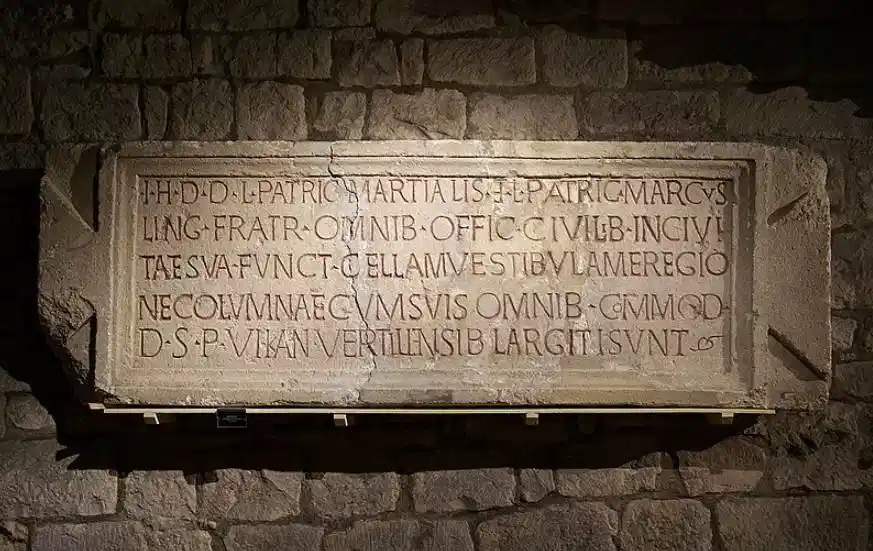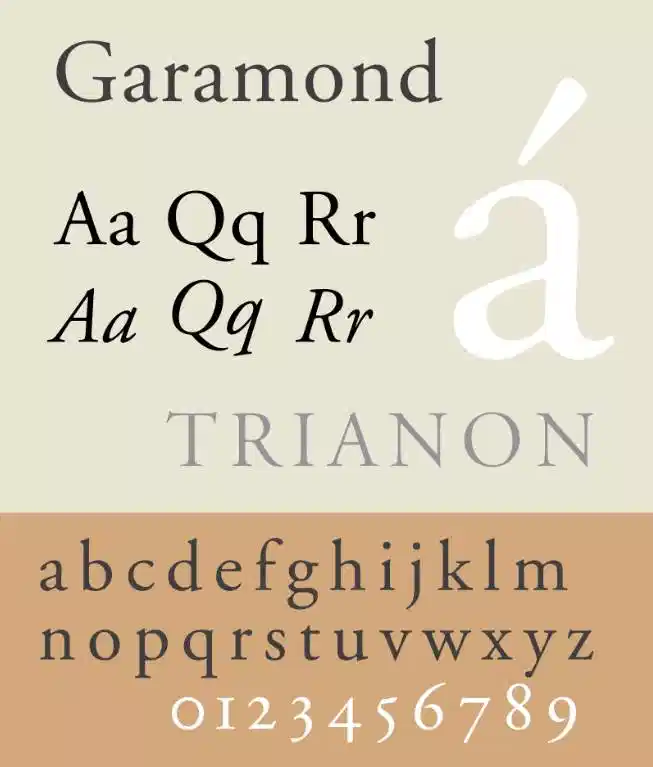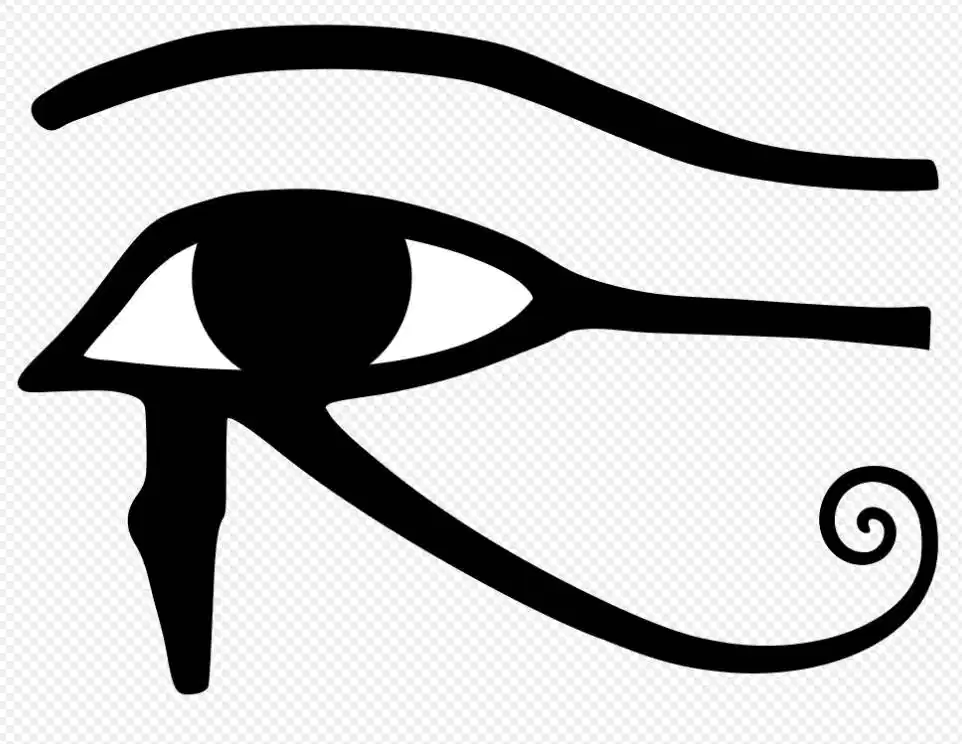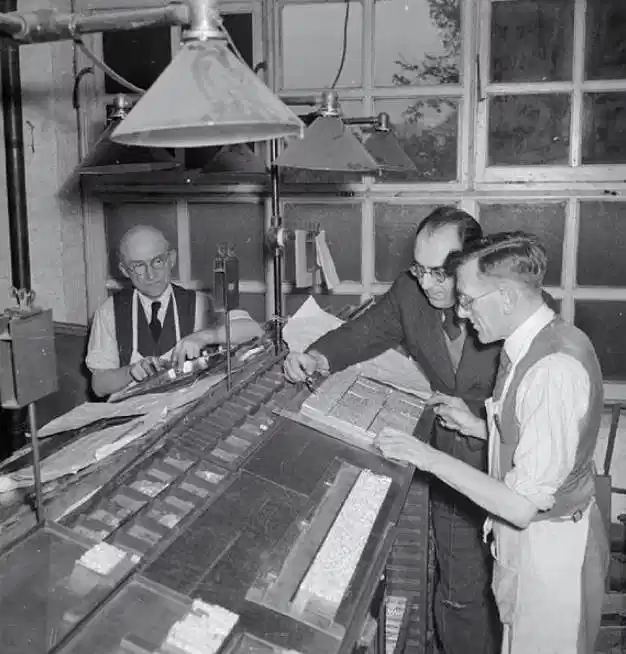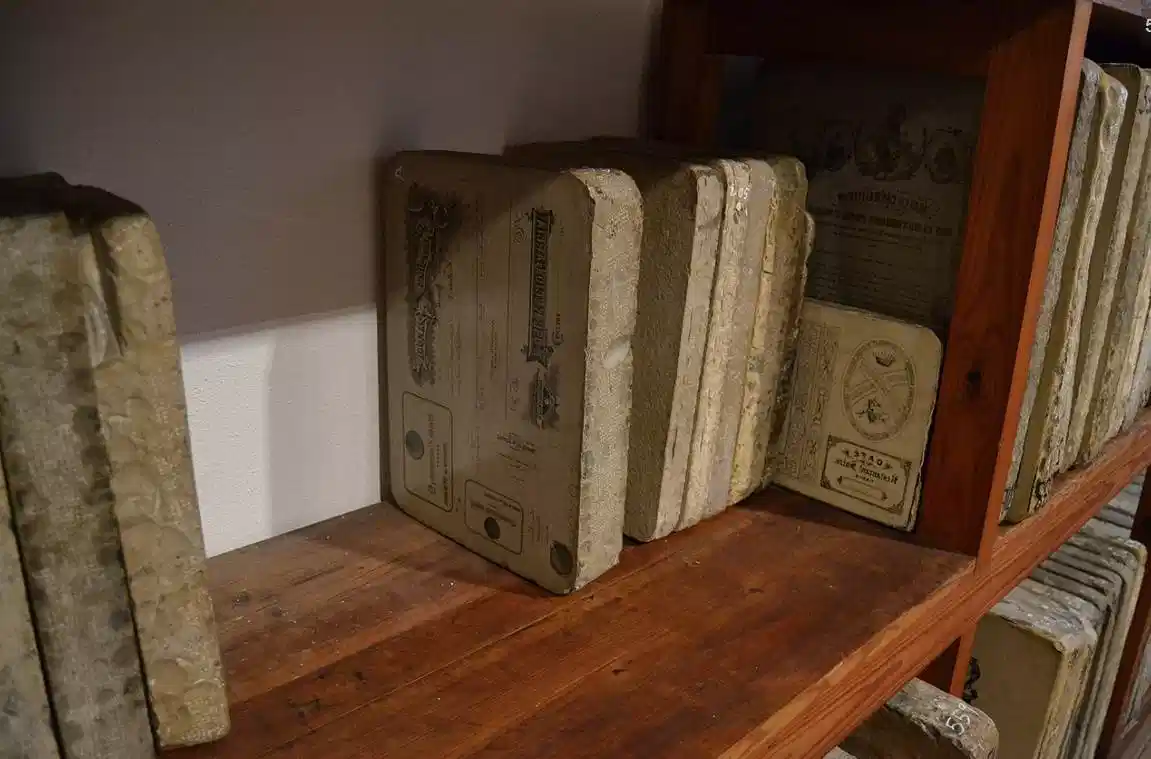
Explorez l'évolution fascinante de la typographie, des premières formes d'écriture à l'invention de Gutenberg et jusqu'aux innovations numériques contemporaines. Découvrez les figures clés, les mouvements artistiques et les enjeux actuels de cet art essentiel
Ce point explore la longue transition entre les premières formes d'écriture et l'invention de la typographie, qui a révolutionné la diffusion des textes.
L'écriture n'est pas apparue du jour au lendemain. C'est un processus lent et progressif qui s'est étalé sur des millénaires.
On distingue plusieurs étapes clés :
Les pictogrammes constituent les premières formes d'écriture connues, remontant au Néolithique, il y a plus de 5000 ans. Ils consistent en des dessins figuratifs représentant des objets concrets du monde réel, tels que le soleil, un arbre, un animal ou un outil. Utilisés notamment en Mésopotamie et en Égypte, ils permettaient de communiquer des informations simples et directes. Cependant, leur principal inconvénient réside dans leur incapacité à exprimer des concepts abstraits, des idées complexes ou des actions, limitant ainsi leur portée et leur capacité à transmettre des messages nuancés. Cette limitation a conduit à l'évolution vers des systèmes d'écriture plus sophistiqués.
Les idéogrammes marquent une évolution par rapport aux pictogrammes en représentant non plus un objet concret, mais une idée ou un concept abstrait. Par exemple, le dessin d'un soleil peut symboliser la lumière, le jour, la chaleur ou même le temps. Cette abstraction permet d'exprimer des notions plus complexes que les simples objets. Néanmoins, les idéogrammes conservent une certaine ambiguïté et leur nombre important rend leur apprentissage et leur utilisation complexes. Ils constituent une étape importante vers des systèmes d'écriture plus performants, mais restent encore limités dans leur capacité à exprimer toute la richesse du langage.
Apparue en Mésopotamie vers 3200 av. J.-C., l'écriture cunéiforme est considérée comme la première véritable forme d'écriture organisée. Elle utilise des signes en forme de clous ou de coins, imprimés sur des tablettes d'argile à l'aide d'un calame, un roseau taillé. Ce système mixte combine des idéogrammes, représentant des idées, et des signes phonétiques, représentant des sons. Cette combinaison permet une plus grande précision et une plus large gamme d'expression. L'écriture cunéiforme a été utilisée pendant plusieurs millénaires et a servi à transcrire plusieurs langues, marquant une avancée majeure dans l'histoire de l'écriture.
Utilisés à partir de 3200 av. J.-C. en Égypte, les hiéroglyphes constituent un système d'écriture complexe et sophistiqué. Ils combinent trois types de signes : des idéogrammes, représentant des concepts ; des phonogrammes, représentant des sons ; et des signes déterminatifs, qui précisent le sens d'un mot et évitent les ambiguïtés. Ce système complexe nécessitait un apprentissage long et approfondi, le réservant à une élite de scribes. Les hiéroglyphes ont joué un rôle déterminant dans la conservation de la culture et de l'histoire égyptiennes, gravés sur les monuments, les papyrus et les objets rituels.
L'alphabet représente une invention majeure attribuée aux Phéniciens vers le XIIe siècle av. J.-C. Son principe fondamental est de représenter chaque son (ou phonème) par un signe unique, une consonne dans l'alphabet phénicien. Les Grecs ont ensuite adopté et adapté cet alphabet en y ajoutant les voyelles, le rendant plus complet et plus précis. L'alphabet grec est à l'origine de l'alphabet latin, qui est aujourd'hui le système d'écriture le plus utilisé au monde. L'alphabet a considérablement simplifié l'écriture, la rendant plus accessible et favorisant ainsi la diffusion du savoir et de la culture.
Le support d'écriture a une influence directe sur la forme et l'évolution de l'écriture :
Les tablettes d'argile, largement utilisées en Mésopotamie dès le IVe millénaire av. J.-C., offraient un support d'écriture à la fois durable et économique. L'argile, abondante dans la région, était façonnée en tablettes humides sur lesquelles les scribes imprimaient des signes cunéiformes à l'aide d'un calame. Une fois séchées au soleil ou cuites au four, ces tablettes devenaient extrêmement résistantes au temps, ce qui explique leur conservation jusqu'à nos jours. L'écriture cunéiforme, avec ses marques en forme de coins, était particulièrement bien adaptée à ce support, permettant une inscription claire et durable. Les tablettes d'argile ont ainsi servi de support pour une grande variété de textes : administratifs, littéraires, religieux et scientifiques.
Inventé en Égypte, le papyrus est un support d'écriture fabriqué à partir de la plante du même nom, le Cyperus papyrus. Les tiges de papyrus étaient découpées en fines lamelles, puis assemblées et pressées pour former des feuilles. Plus léger et plus maniable que l'argile, le papyrus permettait l'écriture à l'encre, à l'aide d'un pinceau ou d'un roseau taillé. Ce support a favorisé le développement de l'écriture et la diffusion du savoir dans l'Égypte antique et au-delà. Cependant, le papyrus est plus fragile que l'argile et se conserve moins bien dans des conditions humides.
Le parchemin, fabriqué à partir de peau d'animal (généralement de mouton, de chèvre ou de veau) spécialement traitée, offre un support d'écriture de qualité supérieure. Plus résistant et plus souple que le papyrus, il permettait l'écriture sur les deux faces et pouvait être plié et relié pour former des livres, les codex. Le parchemin est devenu le support d'écriture privilégié au Moyen Âge, supplantant progressivement le papyrus en Europe. Sa robustesse et sa durabilité ont permis la conservation de nombreux textes importants de cette époque. Le parchemin, bien que plus coûteux à produire que le papyrus, offrait une meilleure qualité et une plus grande longévité.
Avant l'invention de l'imprimerie, tous les textes étaient copiés à la main. La calligraphie, l'art de la belle écriture, occupait une place importante :
L'onciale est un style d'écriture en lettres capitales arrondies, caractérisé par des formes douces et cursives. Utilisée principalement entre le IVe et le VIIIe siècle, elle était particulièrement adaptée à l'écriture sur des supports souples comme le parchemin, avec une plume d'oie taillée en biseau. Ses lettres rondes et sans angles vifs permettaient une écriture plus rapide et plus fluide que les capitales romaines classiques. L'onciale a été largement employée pour la copie de textes bibliques et d'autres ouvrages religieux, contribuant à la diffusion du christianisme. Bien qu'elle ait progressivement décliné face à la caroline, elle a influencé les écritures ultérieures, notamment pour les lettrines et les débuts de chapitres.
La caroline, apparue sous l'impulsion de Charlemagne au VIIIe siècle, représente une rupture majeure dans l'histoire de l'écriture occidentale. Elle se distingue par sa grande lisibilité et sa régularité, grâce à des lettres claires, distinctes et bien proportionnées. La caroline a introduit une distinction claire entre les majuscules et les minuscules, facilitant grandement la lecture et la compréhension des textes. Cette écriture a été diffusée dans tout l'Empire carolingien, contribuant à l'unification culturelle et à la renaissance intellectuelle de l'époque. La caroline est considérée comme l'ancêtre direct de nos minuscules actuelles, et son influence est encore visible dans les caractères d'imprimerie que nous utilisons aujourd'hui.
L'écriture gothique, qui s'est développée à partir du XIIe siècle, marque une évolution stylistique importante par rapport à la caroline. Elle se caractérise par des lettres anguleuses, brisées et verticales, créant un effet visuel dense et ornemental. L'écriture gothique a connu plusieurs variations régionales et stylistiques, telles que la textura, la rotunda, la schwabacher et la fraktur. Elle a été largement utilisée au Moyen Âge pour la copie de manuscrits, les documents officiels et les textes littéraires. Bien que considérée aujourd'hui comme moins lisible que la caroline, l'écriture gothique a marqué son époque et a influencé l'art et l'architecture de la période gothique.
La xylographie est une technique d'impression qui consiste à graver une image ou un texte en relief sur une planche de bois. La planche est ensuite encrée et pressée sur un support (papier ou tissu) pour reproduire l'image ou le texte.
La xylographie a vu le jour en Chine dès le VIIe siècle, sous la dynastie Tang. Elle s'est ensuite progressivement diffusée vers l'ouest, atteignant l'Europe au XIVe siècle, notamment grâce aux échanges commerciaux le long de la Route de la Soie. En Europe, la xylographie a connu un essor important, étant employée pour la production d'images religieuses, souvent vendues comme des objets de piété, de cartes à jouer, très populaires à l'époque, et d'ouvrages illustrés, les "livres xylographiques" ou "incunables xylographiques". Cette technique a ainsi contribué à la diffusion des images et des textes avant l'invention de l'imprimerie à caractères mobiles.
La xylographie a joué un rôle déterminant dans l'évolution des techniques d'impression et a ouvert la voie à l'invention de la typographie par Gutenberg au XVe siècle. En effet, la pratique de la xylographie a permis de comprendre les principes fondamentaux de l'impression en relief, tels que la préparation de la matrice, l'encrage et le pressage sur un support. Les artisans ont ainsi pu développer des techniques d'encrage plus efficaces et perfectionner les presses utilisées pour l'impression. Néanmoins, la xylographie présentait une limitation majeure : chaque page, texte et image, nécessitait la gravure d'une nouvelle planche de bois, ce qui rendait le processus coûteux, long et laborieux, notamment pour les ouvrages de grande taille.
Ce développement permet de comprendre le contexte historique et technique qui a mené à l'invention de la typographie par Gutenberg au XVe siècle, marquant une rupture majeure dans l'histoire de la communication et de la diffusion du savoir.
Ce point central aborde l'invention qui a bouleversé la diffusion de l'information et du savoir en Europe et dans le monde.
Johannes Gutenberg, orfèvre allemand né à Mayence vers 1400, est considéré comme l'inventeur de la typographie moderne. Son innovation majeure réside dans la mise au point des caractères mobiles en plomb.
Son processus, fruit de plusieurs années de recherche, combine plusieurs éléments clés :
Gutenberg a révolutionné la fabrication des caractères d'imprimerie en développant un système ingénieux. Il créa des moules en métal, appelés matrices, dans lesquels il coulait un alliage de plomb, d'étain et d'antimoine. Cet alliage, fusible à basse température et suffisamment résistant pour l'impression, permettait de reproduire chaque caractère (lettre, chiffre, signe de ponctuation) à l'identique et en grande quantité. Cette standardisation des caractères fut une innovation majeure, rendant possible la composition et la recomposition à l'infini des textes. Ce procédé permettait une production beaucoup plus rapide et efficace que la gravure sur bois utilisée auparavant.
Pour imprimer les textes composés avec ses caractères mobiles, Gutenberg adapta une presse en bois, inspirée des presses à vin ou des pressoirs agricoles. Cette presse permettait d'appliquer une pression uniforme sur les caractères encrés et le papier, assurant ainsi une impression nette et homogène. L'adaptation de cette technologie existante à l'imprimerie fut une étape fondamentale. Elle permettait d'exercer une force importante et contrôlée, indispensable pour transférer l'encre des caractères au papier. Cette invention a marqué une avancée technique majeure dans le domaine de l'impression.
Gutenberg a également mis au point une encre spécifique pour l'impression typographique. Cette encre, grasse à base d'huile, était beaucoup plus visqueuse que l'encre utilisée pour l'écriture manuscrite. Cette viscosité était essentielle pour obtenir une impression nette et durable sur le papier, empêchant l'encre de baver et assurant un bon transfert sur le support. La composition de cette encre fut un élément clé du succès de l'imprimerie de Gutenberg. Elle assurait une qualité d'impression supérieure et une meilleure conservation des textes imprimés.
Le composteur est un outil essentiel dans le processus d'impression typographique. Il s'agit d'un instrument permettant d'aligner et de maintenir les caractères mobiles en métal afin de former des lignes de texte. Le typographe utilisait le composteur pour assembler les caractères un par un, en suivant le texte à imprimer. Une fois la ligne composée, elle était transférée sur une galée, un plateau métallique, pour former des colonnes de texte, puis une page entière. Le composteur a donc permis d'organiser et de structurer le texte avant l'impression, assurant une mise en page précise et ordonnée.
L'ensemble de ces innovations constitue un système complet et performant qui permet l'impression de textes en grande quantité et à moindre coût par rapport à la copie manuscrite.
La Bible de Gutenberg, également connue sous le nom de Bible à 42 lignes en raison du nombre de lignes de texte par page, est une œuvre monumentale. Elle représente le premier livre imprimé en Europe grâce à la technique des caractères mobiles inventée par Gutenberg. Imprimée entre 1454 et 1455 à Mayence, en Allemagne, cette bible est un jalon majeur dans l'histoire du livre. Elle symbolise la révolution de l'imprimerie et le passage d'une culture manuscrite à une culture imprimée. Son importance historique et culturelle est immense, marquant le début d'une nouvelle ère dans la diffusion du savoir.
Environ 180 exemplaires de la Bible de Gutenberg ont été imprimés lors de sa première édition. Ce nombre, considérable pour l'époque, témoigne de la capacité de production offerte par l'imprimerie à caractères mobiles. Parmi ces exemplaires, une quarantaine ont été imprimés sur parchemin, un support plus coûteux et plus prestigieux que le papier. L'utilisation du parchemin conférait à ces exemplaires une qualité et une durabilité exceptionnelles. La majorité des exemplaires ont été imprimés sur papier, ce qui a permis une diffusion plus large de l'ouvrage.
La Bible de Gutenberg est reconnue pour la qualité exceptionnelle de son impression. La régularité des caractères, la netteté des traits et la parfaite superposition des encres témoignent du savoir-faire de Gutenberg et de son équipe. La mise en page soignée, avec ses marges harmonieuses et sa typographie élégante, contribue à la beauté de l'ouvrage. Chaque page est un chef-d'œuvre de précision et d'esthétisme, reflétant le souci du détail et la maîtrise technique de Gutenberg. Cette qualité d'impression a servi de modèle pour les imprimeurs des générations suivantes.
La Bible de Gutenberg marque une étape majeure dans l'histoire du livre et de la diffusion du savoir. Son impression a permis une production de livres beaucoup plus rapide et moins coûteuse que la copie manuscrite. Cette innovation a rendu les livres plus accessibles et a contribué à la diffusion des idées et des connaissances à une échelle sans précédent. La Bible de Gutenberg a ainsi joué un rôle essentiel dans la Renaissance et la Réforme, en permettant la circulation des textes religieux et des idées nouvelles. Elle a ouvert la voie à l'imprimerie moderne et à la société de l'information que nous connaissons aujourd'hui.
Après l'invention de Gutenberg, l'imprimerie se diffuse rapidement en Europe, notamment grâce à la dispersion des compagnons de Gutenberg après des difficultés financières.
Les premiers livres imprimés en Europe entre l'invention de Gutenberg et l'année 1500 sont appelés incunables, terme dérivé du latin "incunabula" qui signifie "berceau". Cette appellation souligne le caractère inaugural de ces ouvrages, marquant les débuts balbutiants de l'imprimerie typographique. Les incunables se caractérisent souvent par une imitation des manuscrits médiévaux, tant dans leur mise en page que dans leur typographie. Ils témoignent de la transition entre l'ère du manuscrit et l'ère de l'imprimé. Ils constituent aujourd'hui de précieux témoignages de cette période charnière de l'histoire du livre.
Après l'invention de Gutenberg et les difficultés financières qui ont suivi, notamment le sac de Mayence en 1462, les compagnons et les ouvriers formés par Gutenberg se sont dispersés à travers l'Europe, emportant avec eux leur savoir-faire. Des ateliers d'imprimerie ont ainsi vu le jour dans les grandes villes européennes, devenant rapidement des centres importants de production de livres. Des villes comme Venise, Paris, Cologne, Nuremberg, Strasbourg et Bâle sont devenues des foyers majeurs de l'imprimerie, contribuant à la diffusion rapide de cette nouvelle technologie à travers le continent. Cette dispersion a permis une expansion géographique rapide de l'imprimerie.
L'imprimerie a joué un rôle capital dans l'essor de l'humanisme et de la Renaissance. En permettant la reproduction rapide et à moindre coût des textes, elle a favorisé la diffusion des œuvres des auteurs antiques, redécouverts par les humanistes. Elle a également permis la circulation des nouvelles idées et des découvertes scientifiques, stimulant les débats intellectuels et les échanges entre les savants. L'imprimerie a ainsi contribué à transformer en profondeur la culture et la société européennes, en rendant le savoir plus accessible et en favorisant l'émergence d'une opinion publique. Elle a été un vecteur essentiel de la diffusion des idées nouvelles de la Renaissance.
la diffusion du savoir et la Réforme : L'invention de l'imprimerie a eu des conséquences considérables sur la société et la culture :
L'invention de l'imprimerie a révolutionné la diffusion du savoir en permettant la production massive de livres. Auparavant coûteux et rares, les livres deviennent plus accessibles à un public plus large, favorisant ainsi l'alphabétisation. Cette diffusion des connaissances a stimulé les échanges intellectuels, les débats et les découvertes. L'imprimerie a ainsi contribué à l'émergence d'une société plus instruite et plus ouverte aux idées nouvelles. Elle a permis une démocratisation du savoir sans précédent.
L'imprimerie a joué un rôle important dans la normalisation et la standardisation des langues vernaculaires. En diffusant des textes écrits dans ces langues, elle a contribué à fixer leur orthographe, leur grammaire et leur vocabulaire. L'imprimerie a ainsi favorisé le passage d'une multitude de dialectes locaux à des langues nationales plus unifiées. Ce processus a renforcé les identités culturelles et nationales en Europe. Elle a permis une plus grande cohérence et une meilleure compréhension des textes à travers les régions.
L'imprimerie a été un facteur déterminant dans la diffusion des idées de Martin Luther et de la Réforme protestante au XVIe siècle. Les écrits de Luther, traduits en langues vernaculaires et imprimés en grande quantité, ont touché un large public, remettant en question l'autorité de l'Église catholique. Cette diffusion rapide des idées réformatrices a contribué à la division religieuse de l'Europe. L'imprimerie a ainsi joué un rôle majeur dans un bouleversement religieux et politique majeur.
L'imprimerie a favorisé l'émergence d'une opinion publique en permettant la diffusion rapide et à grande échelle des idées et des débats. Les pamphlets, les journaux et les autres imprimés ont permis la circulation des informations et des opinions, encourageant les discussions et les échanges. Cette circulation de l'information a contribué à la formation d'une conscience collective et à l'émergence d'un espace public de discussion. L'imprimerie a ainsi joué un rôle clé dans le développement de la pensée critique et de la participation citoyenne.
En somme, l'invention de la typographie par Gutenberg a marqué un tournant majeur dans l'histoire de l'humanité. Elle a révolutionné la communication, la diffusion du savoir et a eu des conséquences profondes sur la société, la culture et la politique.
Cette période est marquée par une évolution stylistique importante des caractères typographiques, passant des formes inspirées de l'écriture manuscrite à des formes de plus en plus géométriques et contrastées.
Au XVe siècle, en Italie, les humanistes, passionnés par la redécouverte des textes antiques, ont développé une nouvelle forme d'écriture manuscrite : l'écriture humanistique. Cette écriture, en rupture avec l'écriture gothique alors dominante, se caractérisait par une clarté et une lisibilité renforcées. Inspirée des inscriptions romaines antiques, elle privilégiait des formes rondes et équilibrées, plus faciles à lire que les caractères gothiques anguleux. Cette nouvelle esthétique reflétait l'idéal humaniste de retour aux sources de la culture classique. L'écriture humanistique a ainsi préparé le terrain à une révolution typographique.
Les premiers imprimeurs italiens, notamment Nicolas Jenson à Venise, ont puisé leur inspiration dans l'écriture humanistique pour créer les caractères typographiques dits "romains". Ces caractères se distinguaient par plusieurs éléments clés : les empattements, petites extensions aux extrémités des lettres, le contraste modéré entre les pleins et les déliés (traits épais et fins), et une grande lisibilité. Ces caractéristiques rendaient la lecture plus agréable et plus efficace. Les caractères romains ont rapidement supplanté les caractères gothiques dans l'imprimerie, marquant une étape importante dans l'histoire de la typographie.
En rompant avec les formes gothiques, jugées trop complexes et peu lisibles, elle a ouvert la voie à une esthétique plus classique et plus harmonieuse. Les caractères romains, inspirés de cette écriture, ont incarné cet idéal de clarté et d'équilibre. Cette évolution a profondément influencé l'évolution de la typographie occidentale, les caractères romains étant encore largement utilisés aujourd'hui. L'héritage de l'écriture humanistique continue ainsi de façonner notre perception de la lecture et de l'écriture.
Claude Garamond (vers 1480-1561) est une figure majeure de l'histoire de la typographie. Graveur de caractères et imprimeur français, il est considéré comme l'un des plus grands typographes de tous les temps. Son travail a profondément influencé l'évolution des caractères d'imprimerie. Il a notamment créé des caractères romains d'une qualité exceptionnelle, qui ont connu un succès retentissant à travers l'Europe. Son héritage perdure encore aujourd'hui, témoignant de son génie et de son impact durable sur le monde de l'imprimerie.
Garamond a créé des caractères romains d'une grande élégance et d'une lisibilité remarquable. Ces caractères se distinguent par leur finesse, leur équilibre et leur harmonie. Les formes des lettres sont claires et bien proportionnées, facilitant la lecture et rendant les textes imprimés plus agréables à l'œil. Cette recherche de la perfection esthétique et fonctionnelle a contribué au succès durable de ses créations. Son travail a établi un nouveau standard de qualité dans le domaine de la typographie.
Les caractères de Garamond ont été utilisés pendant des siècles et continuent d'inspirer les typographes contemporains. De nombreuses versions numériques de ses caractères existent aujourd'hui, permettant de les utiliser sur les ordinateurs et dans les logiciels de mise en page. Ces versions numériques perpétuent l'héritage de Garamond et permettent à ses créations de continuer à influencer le monde de la typographie. Son influence est telle qu'elle marque durablement l'histoire de la typographie, en établissant un standard de qualité et d'élégance qui continue de résonner aujourd'hui.
John Baskerville et la recherche de la perfection typographique :
Au XVIIIe siècle, le typographe anglais John Baskerville (1706-1775) apporte des innovations importantes dans la conception des caractères typographiques.
John Baskerville, typographe anglais du XVIIIe siècle (1706-1775), ne s'est pas limité à la création de caractères. Il a également cherché à améliorer l'ensemble du processus d'impression. Pour cela, il a développé une nouvelle technique de fabrication du papier, plus lisse et plus uniforme, permettant une meilleure impression. Il a également perfectionné la presse à imprimer, afin d'obtenir une pression plus homogène sur le papier. Ces innovations ont contribué à améliorer significativement la qualité des impressions, en rendant les textes plus nets et plus précis.
Baskerville est surtout connu pour la création de caractères typographiques dits de "transition". Ces caractères marquent une évolution importante entre les caractères romains classiques, hérités de la Renaissance, et les caractères modernes, qui apparaîtront à la fin du XVIIIe siècle. Les caractères de Baskerville se caractérisent par un contraste plus marqué entre les pleins (traits épais) et les déliés (traits fins), des empattements plus fins et plus horizontaux, et une plus grande régularité des formes. Ces évolutions ont conféré aux caractères une apparence plus élégante et plus raffinée.
Baskerville accordait une importance primordiale à la lisibilité et à l'esthétique de ses caractères. Il recherchait un équilibre parfait entre la forme et la fonction, considérant que la beauté d'un caractère devait servir sa lisibilité. Il a ainsi conçu des caractères à la fois élégants et faciles à lire, ce qui a contribué à leur succès et à leur influence durable. Son souci du détail et sa recherche de l'harmonie ont fait de ses caractères des modèles du genre, influençant profondément l'évolution de la typographie. Son approche a marqué un tournant dans la conception des caractères.
À la fin du XVIIIe siècle et au début du XIXe siècle, les typographes français Firmin Didot (1764-1836) et italien Giambattista Bodoni (1740-1813) ont révolutionné la typographie en développant un nouveau style de caractères, appelé "moderne" ou "Didone". Ce style marquait une rupture nette avec les caractères précédents, en introduisant une esthétique plus géométrique et contrastée. Didot et Bodoni, bien que travaillant indépendamment, ont abouti à des résultats similaires, définissant les canons du style moderne. Leur influence sur la typographie a été considérable et durable.
Les caractères Didot et Bodoni se caractérisent par un contraste très marqué entre les pleins (traits épais) et les déliés (traits fins), créant un effet visuel saisissant. Leurs empattements sont fins et droits, souvent en forme de filets, renforçant l'aspect géométrique. La structure générale des lettres est rigoureuse et précise, dégageant une impression de clarté et de modernité. Ces caractéristiques confèrent aux textes composés en Didot ou Bodoni une élégance formelle et une grande lisibilité, tout en soulignant leur aspect graphique.
Les caractères Didot et Bodoni ont connu un immense succès dès leur apparition et ont influencé la typographie pendant une grande partie du XIXe siècle. Leur esthétique novatrice a séduit les imprimeurs et les éditeurs, qui les ont largement utilisés dans les livres, les journaux et les affiches. Bien que leur popularité ait connu des fluctuations au cours du XXe siècle, ils sont encore utilisés aujourd'hui, notamment dans la presse de luxe, la publicité et l'édition d'art, où leur élégance et leur raffinement sont particulièrement appréciés. Leur héritage continue d'inspirer les designers graphiques contemporains.
L'émergence du style moderne a marqué une rupture significative avec les formes typographiques plus traditionnelles, telles que les caractères romains de Garamond ou les caractères de transition de Baskerville. En privilégiant le contraste, la géométrie et la rigueur, les caractères Didot et Bodoni ont ouvert la voie à une nouvelle esthétique typographique. Cette évolution annonçait la tendance vers des caractères de plus en plus géométriques et contrastés, qui se poursuivra au cours du XIXe et du XXe siècle, notamment avec l'avènement des caractères linéales (sans-serif).
Cette période du XVIe au XVIIIe siècle est, par conséquent, primordiale pour l'histoire de la typographie. Elle voit l'évolution des caractères romains inspirés de l'écriture humanistique, l'émergence des caractères classiques de Garamond, la transition vers des formes plus contrastées avec Baskerville, et enfin l'apparition du style moderne avec Didot et Bodoni. Ces évolutions ont façonné l'esthétique typographique et continuent d'influencer la création de caractères aujourd'hui.
Le XIXe siècle marque une nouvelle étape majeure dans l'histoire de l'imprimerie et de la typographie, avec l'avènement de l'industrialisation et l'apparition de nouvelles techniques et de nouveaux styles.
Ces deux inventions ont profondément transformé les techniques de reproduction d'images et de textes :
Inventée par Alois Senefelder à la fin du XVIIIe siècle, laLa lithographie est une technique d'impression à plat qui utilise une pierre calcaire. L'image est dessinée sur la pierre avec un crayon gras, puis la pierre est traitée chimiquement pour que l'encre adhère uniquement aux parties dessinées. Ce procédé permet une grande finesse de trait et la reproduction d'images complexes, ouvrant la voie à l'illustration de masse et à l'art de l'affiche. La lithographie a permis la diffusion d'images à grande échelle et a eu un impact majeur sur l'art et la communication visuelle. Elle a notamment favorisé l'essor de l'illustration de livres et de la publicité.
Développée au milieu du XIXe siècle, la photogravure a permis de reproduire des images photographiques par des procédés d'impression typographique. Un cliché photographique est transféré sur une plaque de métal (zinc ou cuivre), qui est ensuite gravée chimiquement. Cette technique permet une reproduction fidèle des détails et des nuances de gris des photographies, révolutionnant l'illustration des livres et des journaux. La photogravure a rendu possible l'intégration des photographies dans les supports imprimés, ouvrant de nouvelles perspectives pour l'information et la communication. Elle a marqué une étape essentielle dans l'histoire de la reproduction d'images.
L'automatisation de la composition typographique a permis d'accroître considérablement la vitesse et la productivité de l'imprimerie :
Inventée par Ottmar Mergenthaler en 1886, la Linotype a révolutionné l'industrie de l'imprimerie en automatisant la composition des textes. Son nom, "line-o'-type" (ligne de caractères), décrit parfaitement son fonctionnement : la machine fond des lignes de texte entières en plomb. L'opérateur tape le texte sur un clavier, et la machine assemble automatiquement les matrices des caractères et les fond en une ligne de plomb prête à l'impression. Cette innovation a considérablement accéléré la production de journaux et de livres, rendant l'impression beaucoup plus rapide et économique. La Linotype a permis une diffusion massive de l'information imprimée.
Inventée par Tolbert Lanston en 1887, la Monotype propose une approche différente de la composition typographique automatisée. Au lieu de fondre des lignes entières, elle fond des caractères individuels en plomb, qui sont ensuite assemblés en lignes de texte. Cette méthode offre une plus grande flexibilité que la Linotype, car elle permet de composer des textes complexes avec des caractères de différentes tailles et de différents styles. La Monotype était particulièrement adaptée aux travaux d'impression de haute qualité, tels que les livres d'art et les éditions soignées. Elle a permis une grande précision dans la mise en page et l'utilisation de caractères variés.
Le XIXe siècle voit l'apparition de nouvelles familles de caractères, qui reflètent les évolutions esthétiques et les besoins de la publicité et de l'industrie :
Les égyptiennes, également appelées "slab serif" en anglais, font leur apparition au début du XIXe siècle. Elles se caractérisent par des empattements rectangulaires et épais, leur donnant un aspect massif et affirmé. Ce style typographique évoque l'Égypte antique, alors très en vogue, et a été largement utilisé dans la publicité et l'affichage. Leur forte présence visuelle les rendait idéales pour attirer l'attention et pour les titres percutants. Les égyptiennes ont marqué une rupture avec les styles précédents par leur géométrie et leur impact visuel.
Les antiques, ou "old style", s'inspirent des inscriptions grecques et romaines, renouant avec l'esthétique des caractères classiques. Elles se caractérisent par des empattements triangulaires et un contraste modéré entre les pleins et les déliés. Ce style typographique offre une grande lisibilité et une élégance sobre, ce qui les rendait particulièrement adaptées aux textes courants et aux ouvrages de littérature. Les antiques ont perpétué l'héritage des caractères humanistiques et ont continué à être utilisées tout au long du XIXe siècle. Elles incarnent une certaine tradition typographique.
Les linéales, ou "sans serif" (sans empattements), apparaissent également au XIXe siècle, bien que leur popularité explose au XXe siècle avec l'essor du design moderne. Elles se distinguent par l'absence d'empattements, ce qui leur confère une grande simplicité et une lisibilité renforcée, notamment pour les textes courts et les affiches. Les linéales sont devenues un standard pour les titres, la signalétique et les supports numériques, grâce à leur aspect épuré et contemporain. Elles symbolisent la modernité et l'efficacité dans la communication visuelle. Leur influence est encore très présente dans le design actuel.
Les mouvements artistiques de l'Art Nouveau (fin XIXe - début XXe siècle) et de l'Art Déco (années 1920-1930) ont également influencé la typographie :
L'Art Nouveau, qui s'épanouit entre la fin du XIXe et le début du XXe siècle, est un mouvement artistique caractérisé par des formes organiques, des lignes courbes et une forte inspiration de la nature. Cette esthétique se retrouve également en typographie, où elle se traduit par des caractères ornés, sinueux et décoratifs. Les lettres s'inspirent souvent de formes végétales, avec des arabesques et des volutes. Cette typographie expressive et imaginative était particulièrement utilisée dans les affiches, les titres et les ouvrages d'art. L'Art Nouveau a apporté une grande richesse ornementale à la typographie.
L'Art Déco, qui connaît son apogée dans les années 1920-1930, se distingue par des formes géométriques, des lignes droites et un style plus épuré. En typographie, cela se traduit par des caractères aux formes géométriques, contrastées et élégantes. Les lettres adoptent des formes angulaires, des lignes droites et des motifs stylisés. L'Art Déco privilégie la clarté, la symétrie et l'harmonie des proportions. Cette typographie, souvent utilisée dans la publicité, l'architecture et le design industriel, reflète l'esprit de modernité et de sophistication de l'époque. Elle marque une rupture avec l'exubérance de l'Art Nouveau.
Le XIXe siècle a donc été une période de profondes transformations pour l'imprimerie et la typographie. L'invention de nouvelles techniques d'impression, l'automatisation de la composition et l'apparition de nouvelles familles de caractères ont permis une production massive de textes et d'images, et ont contribué à l'essor de la presse, de la publicité et de la culture de masse.
Le XXe siècle est une période de profonds changements pour la typographie, marquée par l'influence du modernisme, l'essor de la publicité, l'arrivée de nouvelles technologies et la diversification des styles.
Le Bauhaus, école d'art et de design fondée en Allemagne en 1919, a eu une influence majeure sur la typographie du XXe siècle.
Le Bauhaus, fondé en Allemagne en 1919, a profondément marqué l'histoire du design et de la typographie. L'école prônait une esthétique fonctionnelle, rationnelle et géométrique, en rupture radicale avec les ornements et les décorations caractéristiques de l'Art Nouveau. Cette approche mettait l'accent sur la simplicité des formes, la clarté des lignes et l'adéquation de la forme à la fonction. Cette philosophie a influencé tous les domaines du design, de l'architecture aux arts graphiques, et a eu un impact durable sur la typographie moderne. Le Bauhaus a cherché à créer un langage visuel universel et accessible.
Des figures emblématiques du Bauhaus, comme Herbert Bayer et Jan Tschichold, ont joué un rôle essentiel dans le développement des caractères linéales (sans empattements). Ils ont créé des polices aux formes simples et épurées, telles que l'Universal (Bayer) et le Futura (Paul Renner, influencé par le Bauhaus), qui sont devenues des classiques du design typographique. Ces caractères se caractérisent par leur géométrie rigoureuse, leur absence d'ornements et leur grande lisibilité. Ils ont incarné l'idéal du Bauhaus d'une typographie fonctionnelle et moderne. Leur influence est encore visible dans de nombreuses polices contemporaines.
Le Bauhaus a également innové en promouvant l'utilisation combinée de la photographie et de la typographie. Cette approche a permis la création de compositions graphiques dynamiques et innovantes, où le texte et l'image interagissent de manière nouvelle. L'utilisation du photomontage et de la typographie en tant qu'éléments graphiques à part entière a ouvert de nouvelles perspectives dans le domaine de la communication visuelle. Le Bauhaus a ainsi contribué à l'émergence du graphisme moderne, en explorant les possibilités offertes par la combinaison de différents médias. Cette approche a profondément influencé la publicité et le design graphique.
L'influence du Bauhaus se retrouve dans le développement du style typographique international, qui a dominé le design graphique pendant une grande partie du XXe siècle. Ce style privilégie la clarté, la lisibilité et la fonctionnalité, en accord avec les principes du Bauhaus. Les caractères linéales sont devenus un standard, et la mise en page se caractérise par une grille rigoureuse et une hiérarchie visuelle claire. L'héritage du Bauhaus continue d'influencer le design contemporain, en particulier dans les domaines de la typographie, du graphisme et de l'architecture. Son impact sur la culture visuelle est indéniable.
Le XXe siècle a vu l'essor de la publicité et du marketing, qui ont eu un impact important sur la typographie.
L'essor de la publicité au XXe siècle a profondément influencé la typographie, en créant un besoin de caractères spécifiques, plus expressifs et plus accrocheurs. L'objectif principal de la publicité étant d'attirer l'attention du public et de promouvoir un produit ou un service, la typographie a dû s'adapter pour devenir un outil de persuasion visuelle. Les caractères sont devenus plus audacieux, plus originaux et plus distinctifs afin de se démarquer dans un paysage visuel de plus en plus saturé. Cette exigence a stimulé la création de nouvelles formes typographiques et l'expérimentation de styles variés. La typographie est ainsi devenue un élément essentiel de la stratégie publicitaire.
Pour répondre aux besoins spécifiques de la publicité, de nouvelles familles de caractères ont été créées au XXe siècle. Parmi celles-ci, on peut citer les caractères à empattements gras, comme le Clarendon, qui offrent une forte présence visuelle et une grande lisibilité, idéales pour les titres et les slogans publicitaires. On a également vu l'émergence de caractères décoratifs, souvent inspirés de styles historiques, tels que les caractères égyptiens revisités, ou influencés par les mouvements artistiques comme l'Art Déco, avec ses formes géométriques et élégantes. Ces nouvelles familles ont élargi le champ des possibles en matière de typographie publicitaire.
Au XXe siècle, la typographie est devenue un élément clé de l'identité visuelle des marques et des entreprises. Le choix d'une police de caractères spécifique permet de communiquer les valeurs, la personnalité et le positionnement d'une marque. Une typographie bien choisie contribue à créer une image de marque cohérente et mémorable, renforçant la reconnaissance et la fidélité des consommateurs. Les entreprises ont compris l'importance d'investir dans une typographie distinctive pour se différencier de la concurrence. La typographie est ainsi devenue un outil stratégique de communication et de branding. Elle participe à la construction de l'identité visuelle des marques.
L'arrivée de la photocomposition dans les années 1950 a révolutionné les techniques d'impression et a ouvert de nouvelles possibilités pour la typographie.
L'arrivée de la photocomposition dans les années 1950 a marqué une rupture majeure dans l'histoire des techniques d'impression. Cette nouvelle méthode permettait de composer des textes et des images non plus avec des caractères en plomb physiques, mais à l'aide de procédés photographiques. Des matrices de caractères étaient photographiées et projetées sur un support photosensible, permettant de créer une image du texte. Cette innovation a éliminé les contraintes liées à la manipulation du plomb et a ouvert de nouvelles perspectives pour la typographie et la mise en page. La photocomposition a ainsi amorcé la transition vers les techniques d'impression modernes.
La photocomposition a considérablement amélioré la flexibilité dans la mise en page. Contrairement à la composition typographique traditionnelle, qui était limitée par la taille et la disponibilité des caractères en plomb, la photocomposition permettait une plus grande liberté dans le choix des tailles, des styles et des espacements. Il devenait possible de manipuler les caractères avec une précision importante, de les agrandir, de les rétrécir, de les incliner et de les combiner de manière plus créative. Cette flexibilité a favorisé l'expérimentation typographique et a permis la création de mises en page plus dynamiques et plus expressives.
La photocomposition a joué un rôle fondamental dans le développement et l'essor de l'impression offset. Cette technique, qui utilise des plaques photosensibles pour transférer l'encre sur le Papier, est devenue une alternative plus rapide et plus économique que l'impression typographique traditionnelle. La photocomposition, en permettant la création de films ou de plaques précises et de haute qualité, a facilité l'adoption de l'offset par les imprimeurs. Cette transition a contribué à la démocratisation de l'impression en rendant les coûts de production plus abordables et les délais de réalisation plus courts.
L'introduction de la photocomposition et son lien avec l'impression offset ont contribué à une diversification sans précédent des techniques d'impression. L'industrie graphique a connu une période d'expansion et d'innovation, avec l'émergence de nouvelles machines, de nouveaux matériaux et de nouvelles méthodes de production. Cette évolution a eu un impact significatif sur la communication visuelle, en offrant des possibilités renforcées pour la création de supports imprimés de toutes sortes, des livres et des journaux aux affiches et aux emballages. La photocomposition a ainsi marqué une étape clé dans la modernisation de l'industrie graphique.
La typographie suisse, développée dans les années 1950 et 1960, a eu une influence majeure sur le design graphique international.
La typographie suisse, qui a émergé dans les années 1950 et 1960, se distingue par une approche rationnelle et fonctionnelle du design. Elle met l'accent sur la clarté, la lisibilité et la neutralité, cherchant à communiquer l'information de la manière la plus efficace possible. L'ornementation est réduite au minimum, voire totalement absente, au profit d'une structure claire et d'une hiérarchie visuelle bien définie. Cette approche pragmatique et rigoureuse a eu une influence considérable sur le développement du design graphique moderne. Elle privilégie la communication claire et directe.
La typographie suisse utilise principalement des caractères linéales, tels que l'Helvetica (créé par Max Miedinger) et l'Univers (créé par Adrian Frutiger), qui se caractérisent par leur simplicité et leur neutralité. Ces caractères, dépourvus d'empattements, offrent une excellente lisibilité et s'adaptent à de nombreux contextes. De plus, la typographie suisse emploie des grilles de mise en page rigoureuses, qui permettent d'organiser l'information de manière claire et structurée. L'utilisation de ces outils permet de créer des compositions harmonieuses et efficaces.
Le style international, fortement inspiré de la typographie suisse, s'est diffusé dans le monde entier et a profondément influencé le design graphique, la signalétique, la communication visuelle et même le design web. Son approche rationnelle et sa clarté ont été adoptées par de nombreux designers et entreprises à travers le globe. Le style international est devenu un standard en matière de communication visuelle, privilégiant l'efficacité et la lisibilité. Son influence est encore très présente aujourd'hui, témoignant de son impact durable sur le paysage du design. Il a contribué à l'uniformisation de certains codes visuels.
Le XXe siècle a donc été une période de grandes transformations pour la typographie, marquée par l'influence du modernisme, l'essor de la publicité, l'arrivée de nouvelles technologies et la diversification des styles. Ces évolutions ont contribué à façonner la typographie telle que nous la connaissons aujourd'hui. L'influence du Bauhaus et de la typographie suisse, en particulier, reste prégnante dans le design graphique contemporain.
Le XXIe siècle marque une nouvelle révolution pour la typographie, avec l'avènement du numérique et l'évolution constante des technologies.
L'arrivée de l'ordinateur personnel et des logiciels de PAO dans les années 1980 et 1990 a transformé en profondeur le monde de l'imprimerie et de la typographie.
L'arrivée de logiciels tels qu'Adobe PageMaker, QuarkXPress (dans les années 1980 et 1990) puis InDesign (plus tard) a transformé la manière dont les graphistes concevaient et mettaient en page des documents. Ces outils ont permis de réaliser des mises en page complexes directement sur ordinateur, en utilisant des polices numériques et en intégrant des images avec une précision sans précédent. Le travail, auparavant manuel et fastidieux, est devenu beaucoup plus rapide et flexible. L'écran d'ordinateur est devenu l'atelier du graphiste, ouvrant un champ de possibilités créatives immense.
La PAO a démocratisé l'accès à la typographie professionnelle. Auparavant, la composition typographique était un métier spécialisé, nécessitant des équipements coûteux et un savoir-faire technique important. Avec l'arrivée des ordinateurs personnels et des logiciels de PAO, les outils de création et de mise en page sont devenus accessibles à un public beaucoup plus large, incluant les petites entreprises, les indépendants et même les particuliers. Cette démocratisation a favorisé l'émergence de nouveaux talents et a contribué à l'essor du design graphique.
L'ordinateur a également révolutionné la gestion et la diffusion des polices. Auparavant stockées physiquement sous forme de caractères en plomb ou de films, les polices sont devenues des fichiers numériques, faciles à stocker, à copier et à distribuer. Cette numérisation a permis une explosion du nombre de polices disponibles et a facilité leur utilisation dans les logiciels de PAO. Les graphistes ont ainsi pu accéder à une palette typographique beaucoup plus riche et variée, stimulant la créativité et l'innovation dans le domaine de la typographie. La typographie est devenue plus accessible et malléable.
L'ère numérique a vu l'explosion de la création de polices numériques et l'adoption du format OpenType.
Développé à la fin des années 1990, le format OpenType a révolutionné le monde de la typographie numérique. Ce format de police multiplateforme a permis de dépasser les limitations des formats précédents en offrant la possibilité de stocker un nombre beaucoup plus important de caractères dans un seul fichier de police. De plus, l'OpenType a introduit des fonctionnalités typographiques avancées, telles que les ligatures (combinaisons de lettres), les petites capitales, les chiffres elzéviriens (ou chiffres de style ancien) et bien d'autres. Cette innovation a considérablement enrichi les possibilités offertes aux graphistes.
L'OpenType a apporté une plus grande richesse et une plus grande flexibilité dans l'utilisation des polices numériques. Grâce à ses fonctionnalités avancées, les graphistes ont pu exercer un contrôle plus précis sur la typographie, en affinant le rendu du texte et en optimisant la lisibilité. Les ligatures, par exemple, améliorent l'esthétique et la fluidité de la lecture en reliant certaines paires de lettres. Les petites capitales permettent une hiérarchisation plus subtile de l'information. L'OpenType a ainsi ouvert la voie à une typographie plus sophistiquée et plus expressive.
L'ère numérique et l'adoption du format OpenType ont favorisé l'essor de nombreux fondeurs de caractères, des entreprises spécialisées dans la création et la distribution de polices numériques. Ces fondeurs, qu'ils soient indépendants ou appartenant à de plus grandes structures, ont proposé une grande variété de polices, allant des classiques revisités aux créations les plus originales et expérimentales. Cette abondance de choix a permis aux graphistes de trouver la police parfaite pour chaque projet, contribuant à la diversification et à la richesse du paysage typographique actuel. La concurrence a aussi stimulé l'innovation et la qualité des polices.
L'essor d'Internet et du World Wide Web a posé de nouveaux défis et de nouvelles opportunités pour la typographie.
Aux débuts du World Wide Web, les possibilités typographiques étaient extrêmement limitées. Les navigateurs web ne pouvaient afficher que les polices installées sur l'ordinateur de l'utilisateur. Cela signifiait que les concepteurs de sites web devaient se contenter d'un nombre restreint de polices "systèmes" (comme Times New Roman, Arial ou Verdana), dont le rendu pouvait varier d'un système d'exploitation à l'autre. Cette contrainte limitait considérablement la créativité et l'identité visuelle des sites web. L'uniformité typographique était de mise, au détriment de l'esthétique et de la communication.
L'arrivée des polices web (Webfonts) et des feuilles de style en cascade (CSS) a marqué une véritable révolution pour la typographie sur le web. Les polices web ont permis d'intégrer des polices personnalisées directement dans les pages web, offrant ainsi une liberté créative beaucoup plus grande aux webdesigners. Les CSS ont quant à eux fourni les outils nécessaires pour contrôler l'apparence du texte, en définissant la police, la taille, la couleur, l'interlignage et d'autres propriétés typographiques. Cette combinaison a permis de créer des expériences web plus riches et plus expressives.
Des services tels que GGoogle Fonts, Adobe Fonts et Font Squirrel ont considérablement démocratisé l'accès aux polices web. Ces plateformes proposent des milliers de polices, gratuites ou payantes, prêtes à être intégrées dans les sites web. Google Fonts, en particulier, offre une vaste bibliothèque de polices open source, facilitant leur utilisation et leur diffusion à grande échelle. Ces services ont rendu la typographie de qualité accessible à tous les concepteurs web, même ceux disposant de budgets limités. La diversité typographique sur le web s'en est trouvée grandement enrichie.
Les CSS (Cascading Style Sheets) offrent un contrôle précis sur l'apparence du texte sur les pages web. Grâce aux CSS, les concepteurs peuvent définir avec précision la police de caractères à utiliser, sa taille, son style (gras, italique, etc.), sa couleur, l'interlignage, l'espacement entre les lettres, l'alignement et bien d'autres propriétés. Cette granularité permet de créer des mises en page typographiques sophistiquées et d'optimiser la lisibilité du texte sur différents supports et écrans. Les CSS sont devenus un outil indispensable pour la mise en page web moderne.
Le design numérique et les nouvelles technologies continuent d'influencer l'évolution de la typographie.
L'essor des écrans haute résolution, tels que les écrans Retina et les écrans 4K, a eu un impact significatif sur la typographie. Ces écrans, offrant une densité de pixels beaucoup plus élevée, permettent d'afficher des caractères avec une finesse et un niveau de détail inégalés. Les polices peuvent ainsi être conçues avec des traits plus fins, des courbes plus douces et des détails plus subtils, améliorant considérablement la lisibilité et l'esthétique du texte à l'écran. Cette évolution a encouragé la création de nouvelles polices optimisées pour les écrans haute résolution, tirant pleinement parti de leurs capacités.
Les technologies d'animation et d'interactivité ont ouvert de nouvelles perspectives passionnantes pour la typographie. Il est désormais possible de créer des caractères animés, qui se transforment, se déplacent ou réagissent aux interactions de l'utilisateur. La typographie devient ainsi un élément dynamique et interactif, capable de renforcer le message, de créer des effets visuels surprenants et d'améliorer l'expérience utilisateur. Ces nouvelles formes d'expression typographique sont particulièrement présentes dans le design web, les applications mobiles et les jeux vidéo.
L'intelligence artificielle (IA) et l'apprentissage automatique (machine learning) sont de plus en plus utilisés dans le domaine de la typographie. L'IA peut être employée pour créer des polices génératives, en analysant des milliers de caractères existants pour en générer de nouveaux, ou pour optimiser la lisibilité des textes, en ajustant automatiquement l'espacement entre les lettres et les lignes en fonction du contexte. Ces technologies ouvrent des perspectives fascinantes pour l'automatisation et l'innovation dans le domaine de la typographie.
La réalité virtuelle (VR) et la réalité augmentée (AR) offrent de nouvelles expériences typographiques immersives. Dans les environnements VR et AR, la typographie peut être intégrée dans des espaces 3D, interagir avec l'environnement et réagir aux mouvements de l'utilisateur. Ces technologies permettent de créer des expériences narratives et interactives uniques, où la typographie joue un rôle central dans l'immersion et l'engagement de l'utilisateur. Ces nouvelles formes d'expression typographique sont encore en développement, mais elles promettent de transformer notre perception du texte et de l'espace.
Aujourd'hui, la typographie se caractérise par une grande diversité de styles et d'usages.
Aujourd'hui, on observe un regain d'intérêt pour les styles typographiques classiques et historiques. Les polices à empattements (serifs), autrefois considérées comme démodées par certains, connaissent un véritable retour en grâce. Cependant, ces styles ne sont pas simplement reproduits à l'identique. Ils sont revisités et adaptés aux outils numériques, bénéficiant des avancées technologiques pour offrir une meilleure lisibilité à l'écran et une plus grande flexibilité d'utilisation. Cette réinterprétation des classiques témoigne d'une volonté de renouer avec l'héritage typographique tout en l'inscrivant dans la modernité.
En parallèle du retour aux classiques, de nouvelles tendances typographiques émergent, repoussant les limites de la créativité. La typographie expérimentale explore des formes non conventionnelles, jouant sur les textures, les déformations et les effets visuels pour créer des compositions uniques et expressives. La typographie variable offre une flexibilité sans précédent en permettant d'ajuster les paramètres d'une police (épaisseur, largeur, inclinaison) à l'infini. La typographie cinétique, quant à elle, utilise l'animation et le mouvement pour donner vie aux caractères. Ces nouvelles tendances témoignent d'une volonté d'innovation et d'expérimentation constante dans le domaine de la typographie.
La typographie est devenue un outil transversal, utilisé dans une multitude de domaines. On la retrouve bien sûr dans l'édition traditionnelle (livres, magazines, journaux), mais aussi dans la publicité, le web design, le design d'interface (UI), la signalétique, le packaging , le branding et bien d'autres. Chaque domaine d'application requiert une approche typographique spécifique, adaptée au support, au message et au public cible. Cette polyvalence témoigne de l'importance de la typographie dans la communication visuelle contemporaine.
Aujourd'hui, la typographie est reconnue comme un élément essentiel de la communication visuelle. Elle ne se limite plus à la simple transmission d'information textuelle. Elle contribue activement à l'identité des marques, en véhiculant des valeurs, un ton et une personnalité. Elle influence également l'expérience utilisateur, en améliorant la lisibilité, la navigation et l'engagement. Le choix d'une police, son utilisation et sa mise en page sont donc des décisions stratégiques qui ont un impact direct sur la perception et l'efficacité d'un message. La typographie est devenue un outil puissant au service de la communication.
En définitive, l'ère numérique a profondément transformé la typographie, en la rendant plus accessible, plus diversifiée et plus interactive. Les nouvelles technologies continuent d'ouvrir de nouvelles perspectives et de nouveaux usages pour la typographie, qui reste un élément essentiel de la communication visuelle au XXIe siècle.
Cette section met en lumière les contributions essentielles de personnalités qui ont façonné l'histoire de la typographie, de l'invention de l'imprimerie aux créations contemporaines.
Johannes Gutenberg (vers 1400-1468) est considéré comme l'inventeur de l'imprimerie typographique à caractères mobiles en Europe, une innovation majeure qui a révolutionné la diffusion du savoir. Son apport fondamental réside dans la mise au point d'un système complet et ingénieux comprenant des caractères mobiles en plomb, permettant de composer des textes réutilisables à l'infini, une presse à imprimer adaptée, inspirée du pressoir à vin, et une encre typographique grasse et résistante, spécialement conçue pour l'impression sur papier. Cette invention a permis une production de livres beaucoup plus rapide et moins coûteuse que la copie manuscrite, ouvrant ainsi l'accès à la lecture à un public plus large. Son œuvre la plus emblématique est sans conteste la Bible de Gutenberg, également appelée Bible à 42 lignes, premier livre imprimé en Europe avec cette technique et chef-d'œuvre de l'incunable, marquant le début d'une nouvelle ère dans l'histoire du livre et de la communication.
Claude Garamond (vers 1480-1561), graveur de caractères et imprimeur français, est une figure majeure de la typographie de la Renaissance. Il est le créateur de caractères romains d'une grande élégance et d'une lisibilité exceptionnelle, inspirés de l'écriture humanistique, un style calligraphique qui mettait l'accent sur la clarté et l'équilibre des formes. Ses créations typographiques, diffusées dans toute l'Europe grâce à l'essor de l'imprimerie, ont servi de modèle pendant des siècles et influencent encore profondément la typographie actuelle, comme en témoignent les nombreuses adaptations numériques de ses caractères. L'impact de Garamond est considérable : il a défini un standard de qualité et d'élégance pour les caractères romains, contribuant ainsi à l'évolution et à la sophistication de l'art typographique.